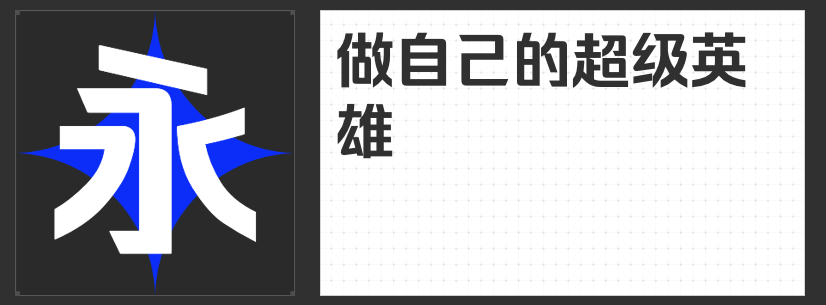
电商设计新势力:四款风格化字库字体推荐
在电商视觉竞争白热化的当下,字体选择已成为品牌差异化表达的关键要素。本文精选四款兼具艺术性与功能性的专业字库字体,从手写温度到几何张力,为电商设计提供多元化的视觉解决方案。
一、字恋狂风摇简 粗体
这款字体以"被风吹过的形态"为设计理念,通过失衡的笔画比例与摇曳的线条节奏,构建出独特的动态美学。其手写质感并非简单模仿毛笔痕迹,而是通过数字化算法精准控制笔画抖动幅度,在保持文字可读性的同时,传递出温暖治愈的视觉氛围。特别适合母婴、文创、食品等需要营造情感共鸣的品类,能有效拉近与消费者的心理距离。
二、励字志向黑简 中粗
作为圆体与黑体的创新融合体,这款字体在保持黑体结构稳定性的基础上,通过0.8mm外圆角处理软化了传统黑体的机械感。中宫适度扩张的设计既保证了屏显清晰度,又为文字注入呼吸感。其5级字重系统可完美适配从商品详情页正文到促销横幅标题的全场景需求,尤其适合3C数码、智能家居等科技类产品的视觉表达。
三、励字勇敢黑简 特黑
这款专为电商标题设计的特黑字体,采用12px超粗笔画与15°斜切收笔的组合策略,在保证远距离识别性的同时,通过几何化处理消除传统黑体的笨重感。其独特的"去尖角"设计使文字在密集排版时仍能保持视觉连贯性,特别适合运动户外、汽车配件等需要强化品牌力量感的品类,能有效提升点击转化率。
四、励字超级勇士简 大粗
突破传统黑体的庄重框架,这款字体通过0.3mm笔画微调技术,在保持严谨结构的同时赋予文字优雅气质。其创新的"弹性中宫"设计可根据排版空间自动调整字面率,在保持60字/行的最佳阅读密度的同时,实现从移动端到户外广告的无缝适配。推荐用于奢侈品、美妆等需要传递精致感的品类视觉系统。
这四款字体均通过专业字库团队的视觉平衡算法优化,在保证艺术表现力的同时,严格遵循电商设计的可读性、适配性、扩展性三大原则。设计师可根据品牌调性选择单款字体建立视觉记忆点,或通过家族字体的组合运用构建完整的品牌字效体系,在激烈的市场竞争中打造独具辨识度的视觉语言。